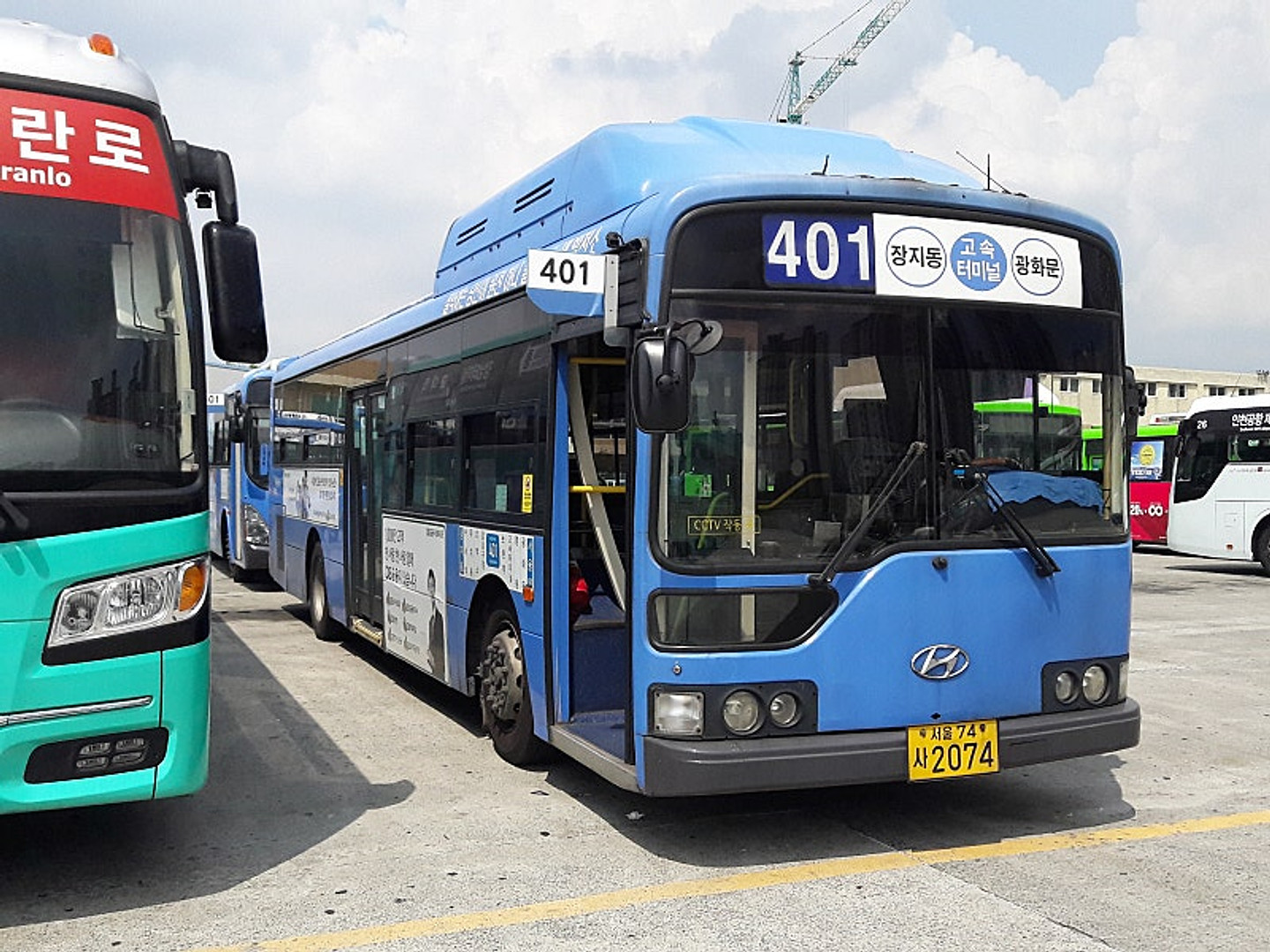
서울버스에 잘 쓰이는 폰트 종류를 다 찾아도 다 안 맞네요 정말 궁굼합니다!
윤고딕 140
1. 윤고딕 140 -> 시안성이 좋아 많이 쓰이는 노선번호 폰트 2. Adobe Garamond Pro -> 서울시내버스 체계개편 당시 서울시내버스 B.I. 노선번호 표준 폰트 3. Times New Roman -> Windows 설치시 기본으로 제공되는 폰트로 Adobe Garamond Pro 대체 폰트로 가장 널리 사용 4. Century Gothic -> 경기도 G-Bus B.I. 노선번호 표준 폰트 5. Dinmed Regular -> 요즘들어 서울시내버스에 적용하는 신규 노선번호 표준 폰트